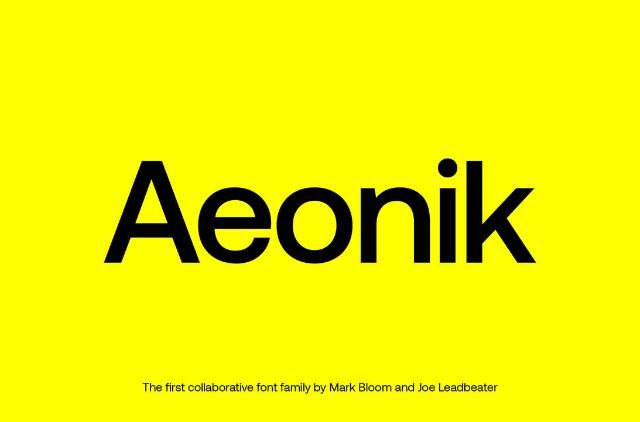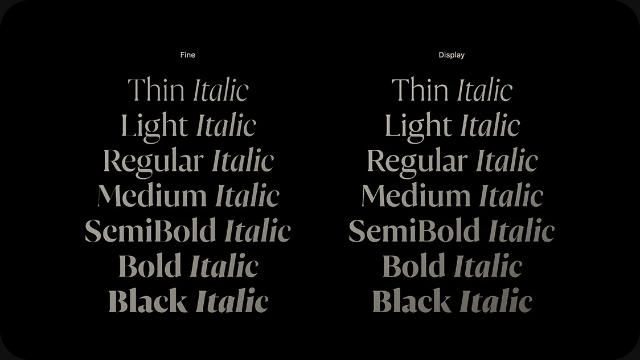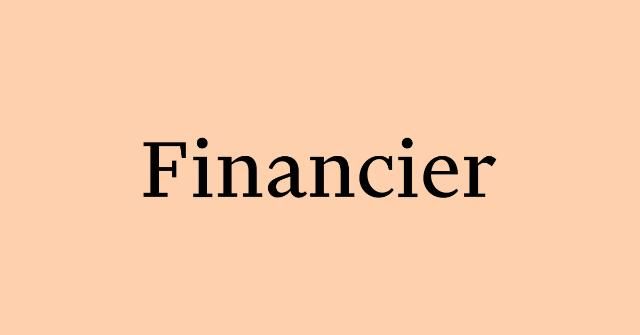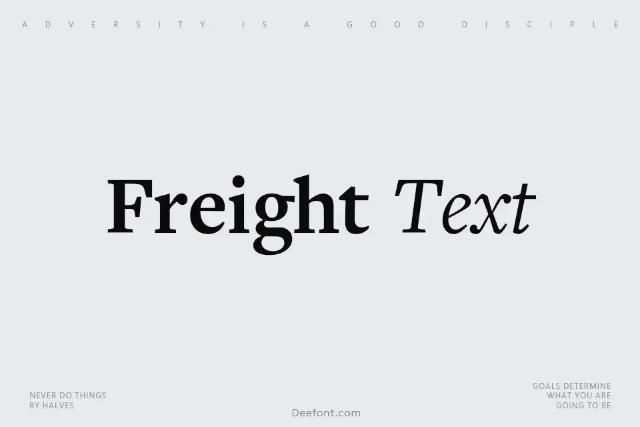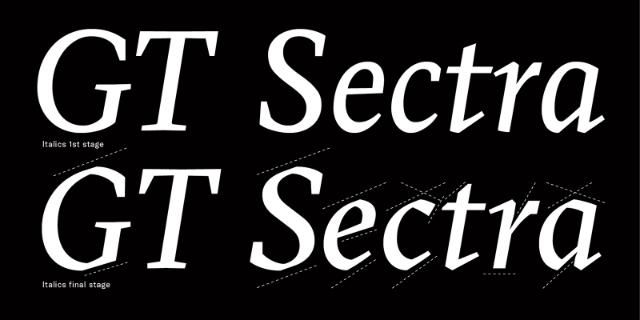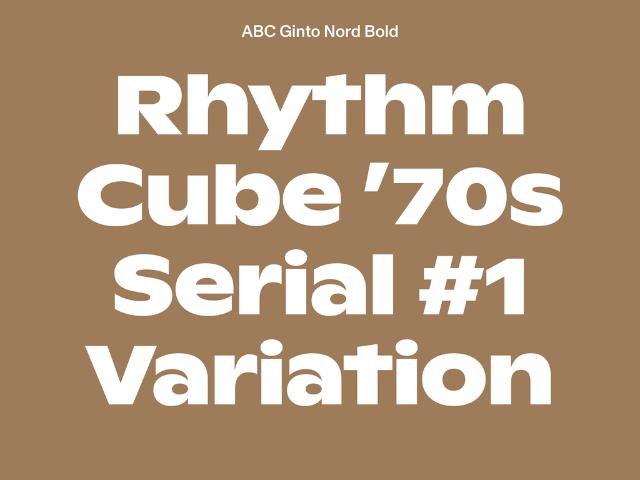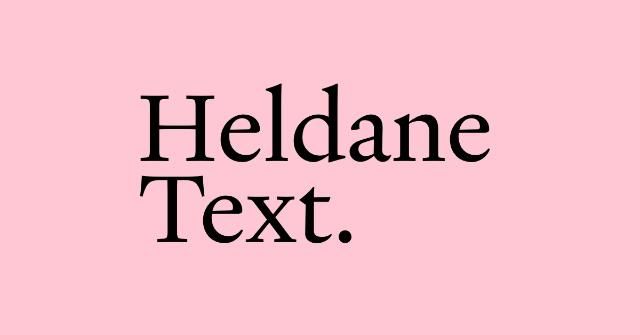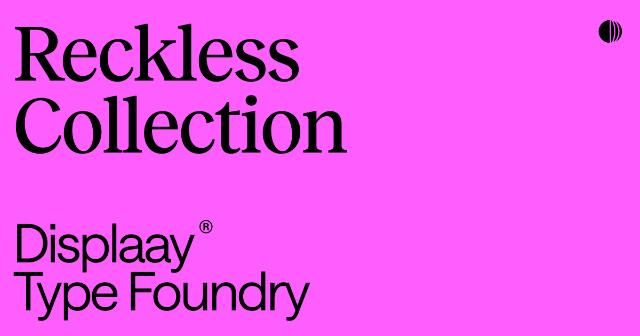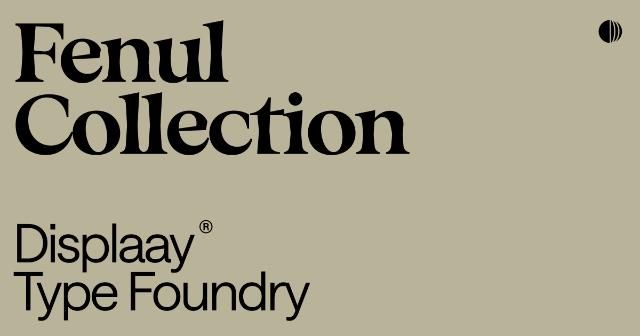
Tổng hợp 17+ Font chữ hiện đại dẫn đầu xu hướng thiết kế
Trong thế giới thiết kế đương đại, Typography không chỉ đơn thuần là công cụ truyền tải văn bản, mà còn là “linh hồn” định hình phong cách và ngôn ngữ của một thương hiệu. Việc lựa chọn một bộ phông chữ xuất sắc có sức mạnh xoay chuyển toàn bộ cục diện của một dự án, biến một bản thiết kế bình thường trở thành một tác phẩm nghệ thuật mang đậm dấu ấn thị giác.
Bài viết này sẽ đưa bạn bước vào thế giới của nghệ thuật con chữ với bộ sưu tập 17+ font chữ hiện đại, cao cấp nhất, được tuyển chọn khắt khe từ các Type Foundry danh tiếng trên toàn cầu. Đây chính là “vũ khí bí mật” giúp các Designer chuyên nghiệp chinh phục mọi ánh nhìn và nâng tầm nhận diện thương hiệu một cách trọn vẹn nhất.
Tại sao các thiết kế cần sử dụng Font chữ hiện đại?
Không phải ngẫu nhiên mà các tập đoàn lớn và các agency hàng đầu liên tục cập nhật và làm mới hệ thống Typography của họ. Việc ứng dụng các font chữ hiện đại mang lại những giá trị cốt lõi không thể thay thế:
• Tạo ấn tượng thị giác mạnh mẽ, chuyên nghiệp: Một font chữ được thiết kế chuẩn mực với tỷ lệ vàng sẽ ngay lập tức tạo ra sự tin cậy. Các nét cắt sắc sảo, độ tương phản tinh tế giúp bản thiết kế của bạn thoát khỏi sự rập khuôn, mang lại một diện mạo đẳng cấp và thời thượng.
• Tối ưu hóa khả năng đọc trên các thiết bị kỹ thuật số (UI/UX): Trong kỷ nguyên số, nội dung của bạn sẽ được hiển thị trên hàng loạt màn hình với kích thước khác nhau. Các font chữ hiện đại được tối ưu hóa “pixel-perfect”, đảm bảo trải nghiệm đọc mượt mà, rõ ràng từ những banner khổng lồ cho đến giao diện mobile nhỏ gọn.
• Thể hiện đúng “tính cách” và đẳng cấp của thương hiệu: Mỗi kiểu chữ mang một tần số cảm xúc riêng. Một font chữ Serif tinh xảo sẽ cất tiếng nói của sự xa xỉ, di sản; trong khi một font Sans-Serif tối giản lại đại diện cho sự vươn lên của công nghệ và tinh thần đổi mới. Chữ viết chính là người phát ngôn thầm lặng cho bản sắc thương hiệu.
Top 17+ Font chữ hiện đại “Must-have” cho Designer
Để giúp bạn dễ dàng tra cứu và lựa chọn, chúng tôi đã hệ thống hóa và phân loại 17 font chữ xuất sắc này thành 3 nhóm cấu trúc chính, phục vụ chính xác cho từng mục đích và phong cách thiết kế khác nhau.
Nhóm Modern Sans-Serif (Font không chân: Tối giản, Sạch sẽ, Đậm chất Tech & UI)
Đây là nhóm font đại diện cho sự cấp tiến. Lược bỏ đi các chi tiết thừa, nhóm Sans-Serif mang lại một không gian thiết kế thoáng đãng, tập trung tối đa vào thông điệp và đặc biệt hoàn hảo cho thiết kế giao diện.
Mont (Font Fabric)
Đến từ nhà Font Fabric danh tiếng, Mont nổi bật với cấu trúc hình học (Geometric) hoàn hảo và cực kỳ sắc nét. Điểm đặc biệt của Mont nằm ở phần x-height (chiều cao chữ x) lớn và các nét nhọn đặc trưng ở một số ký tự. Đây là sự lựa chọn lý tưởng cho các tiêu đề (Headline) cần sự chú ý, dứt khoát nhưng vẫn giữ được nét thanh lịch.
mont
Aeonik Pro (Cotype Foundry)
Nếu bạn đang tìm kiếm một “người hùng thầm lặng”, Aeonik Pro chính là câu trả lời. Mang một vẻ đẹp trung tính, hiện đại và không phô trương, font chữ này tạo ra sự cân bằng hoàn hảo dù được sử dụng cho các khối văn bản dài (Body text) hay hệ thống giao diện UI/UX phức tạp. Nó làm nền tảng vững chắc để các yếu tố đồ họa khác tỏa sáng.
Aeonik Pro Cotype Foundry
Whyte (Dinamo)
Sản phẩm đến từ Dinamo là một nét chấm phá đầy thú vị. Whyte sở hữu các nét cắt (ink traps) độc đáo và mượt mà, tạo nên một cá tính vừa mang tính kỹ thuật, vừa thân thiện. Đây là “chân ái” cho hệ thống nhận diện thương hiệu công nghệ, các ứng dụng SaaS hoặc các startup muốn thể hiện sự đột phá.
font Whyte
Plain (Optimo)
Đúng như tên gọi, Plain từ Optimo là đỉnh cao của sự cực giản. Cấu trúc hình học linh hoạt của nó loại bỏ mọi yếu tố rườm rà, mang lại một tổng thể cực kỳ “sạch sẽ”. Font chữ này vô cùng linh hoạt, dễ dàng thích ứng với các thiết kế mang âm hưởng Swiss Design hoặc phong cách Minimalism.
Ginto (Dinamo)
Một đại diện xuất sắc khác từ Dinamo. Ginto là một sự giao thoa tuyệt vời giữa sự cứng cáp, vững chãi của hình học khối và những đường cong vô cùng mềm mại, uyển chuyển. Sự tương phản nội tại này giúp Ginto vừa thân thiện lại vừa mang đậm tính đương đại, rất phù hợp cho các chiến dịch tái định vị thương hiệu (Rebranding).
Ginto Dinamo
Nhóm Modern Serif (Font có chân: Sang trọng, Thanh lịch, Đậm chất Editorial/Art)
Sự trở lại mạnh mẽ của Modern Serif trong những năm gần đây đã định nghĩa lại khái niệm về sự sang trọng. Chúng không còn già cỗi, mà được tinh chỉnh với độ tương phản cao, mang lại cảm giác nghệ thuật, quyền lực và cực kỳ tinh tế.
Financier (Klim Type Foundry)
Được thiết kế ban đầu cho tờ Financial Times, Financier tỏa ra một khí chất quyền lực, đĩnh đạc và vô cùng thanh lịch. Sự kết hợp giữa tỷ lệ cổ điển và các đường nét dứt khoát khiến font chữ này trở thành lựa chọn số 1 cho các tạp chí tài chính, báo chí cao cấp hoặc các ấn phẩm doanh nghiệp tầm cỡ.
Financier Klim Type Foundry
Reckless (Displaay)
Reckless mang trong mình hơi thở cổ điển nhưng được tái sinh dưới lăng kính hiện đại. Điểm nhấn của nó nằm ở độ tương phản nét thanh – nét đậm cực kỳ rõ ràng, tạo ra nhịp điệu thị giác lôi cuốn. Đây là một font chữ tuyệt vời cho các dự án mang tính tự sự hoặc thiết kế Editorial.
Reckless Displaay
GT Sectra (Grilli Type)
Sắc sảo và góc cạnh, GT Sectra như một bản hòa tấu giữa typography kỹ thuật số và phong cách của những chiếc bút thư pháp hiện đại. Các đường cắt sắc lẹm của nó tạo ra một nguồn năng lượng mạnh mẽ, rất phù hợp cho các bìa sách, tạp chí nghệ thuật hoặc những thương hiệu muốn thể hiện sự gai góc, độc lập.
GT Sectra Grilli Type
Flecha (R-Typography)
Flecha là một typeface ghi điểm bởi sự rõ ràng và cấu trúc cứng cáp, nhưng không hề đánh mất đi sự thanh thoát vốn có của dòng Serif. Nhờ sự tối ưu về tỷ lệ, font chữ này hoạt động cực kỳ tốt ở các kích thước nhỏ, duy trì tính dễ đọc tối đa.
font Flecha.jfif
Nice (Fontwerk)
Chỉ một từ để miêu tả Nice: Cực kỳ quyến rũ. Font chữ này mang lại một cảm giác xa hoa, bay bổng và vô cùng mềm mại. Nó là mảnh ghép hoàn hảo để tôn vinh sự tinh tế trong các thiết kế thuộc ngành thời trang, mỹ phẩm, nữ trang hoặc các thương hiệu lifestyle cao cấp.
BetterImage 1779074587635
Ivyora (Ivy Foundry)
Ivyora cuốn hút người xem bởi sự tinh tế tột bậc cùng độ tương phản nét chữ cực cao (High-contrast Serif). Những nét cong uốn lượn kết hợp với nét thanh mỏng như sợi chỉ tạo nên một tổng thể vô cùng lãng mạn và quý phái.
Ivyora Ivy Foundry.jfif
Freight (Joshua Darden)
Freight mang lại cảm giác ấm áp, gần gũi với mức độ tối ưu hóa cho việc đọc (readability) đạt mức xuất sắc. Hơn thế nữa, bộ family font của Freight vô cùng đồ sộ (Text, Display, Micro, Sans…), cho phép bạn xây dựng một hệ thống phân cấp thông tin trọn vẹn chỉ với một gia đình chữ.
Freight Joshua Darden
Heldane (Klim Type Foundry)
Chịu ảnh hưởng sâu sắc từ phong cách Phục Hưng nhưng Heldane đã được nhà thiết kế Kris Sowersby tinh chỉnh, mài giũa để trở nên cực kỳ sắc nét và phù hợp với kỷ nguyên số. Nó mang lại sự sang trọng, lịch lãm nhưng không hề lỗi thời.
Heldane
Canela (Commercial Type)
Canela là một tác phẩm nghệ thuật thực sự khi lơ lửng nằm giữa ranh giới của Serif và Sans-serif (thường được gọi là Flare-serif). Các nét chữ lả lướt, bay bổng mang đậm tính nghệ thuật khiến Canela luôn là ưu tiên hàng đầu cho các chiến dịch thời trang lớn và các tạp chí phong cách sống hạng sang.
Canela images 03c 02
Nhóm Modern Display (Font hiển thị: Phá cách, Ấn tượng mạnh)
Khi bạn cần một tiếng hét thay vì một lời thì thầm, hãy dùng Display font. Chúng sinh ra không phải để làm khối văn bản dài, mà để phá vỡ các quy tắc, tạo điểm nhấn bùng nổ và thu hút sự chú ý ngay lập tức.
FH Total (Typografische)
Độc lạ, có phần nổi loạn và bất quy tắc. FH Total vượt ra khỏi những giới hạn typography thông thường. Nó sinh ra để dành riêng cho các thiết kế poster sự kiện, ấn phẩm truyền thông sáng tạo hay những chiến dịch quảng cáo cần sự đột phá mạnh mẽ về mặt thị giác.
FH Total Typografische
Fenul (Display)
Fenul sở hữu những đường nét cá tính và cấu trúc con chữ khác biệt. Sử dụng Fenul làm điểm nhấn (Headline) sẽ giúp bản thiết kế của bạn có một “hook” (điểm móc) thị giác vững chắc, khiến người xem không thể rời mắt.
font Fenul Display
Salina (Font Fabric)
Linh hoạt và mang tính xu hướng cao, Salina đem lại cảm giác chuyển động nhịp nhàng trên từng con chữ. Đây là một typeface phản ánh rất rõ ngôn ngữ thiết kế của tương lai, phù hợp cho các nhãn hàng hướng tới giới trẻ hoặc các chiến dịch Marketing mang tính viral.
Salina Font Fabric
Bằng việc làm chủ và linh hoạt ứng dụng Top 17+ font chữ hiện đại từ các Type Foundry uy tín, bạn đã nắm trong tay chìa khóa để kiến tạo nên những không gian thiết kế đậm chất chuyên nghiệp, có khả năng kết nối sâu sắc với người xem.